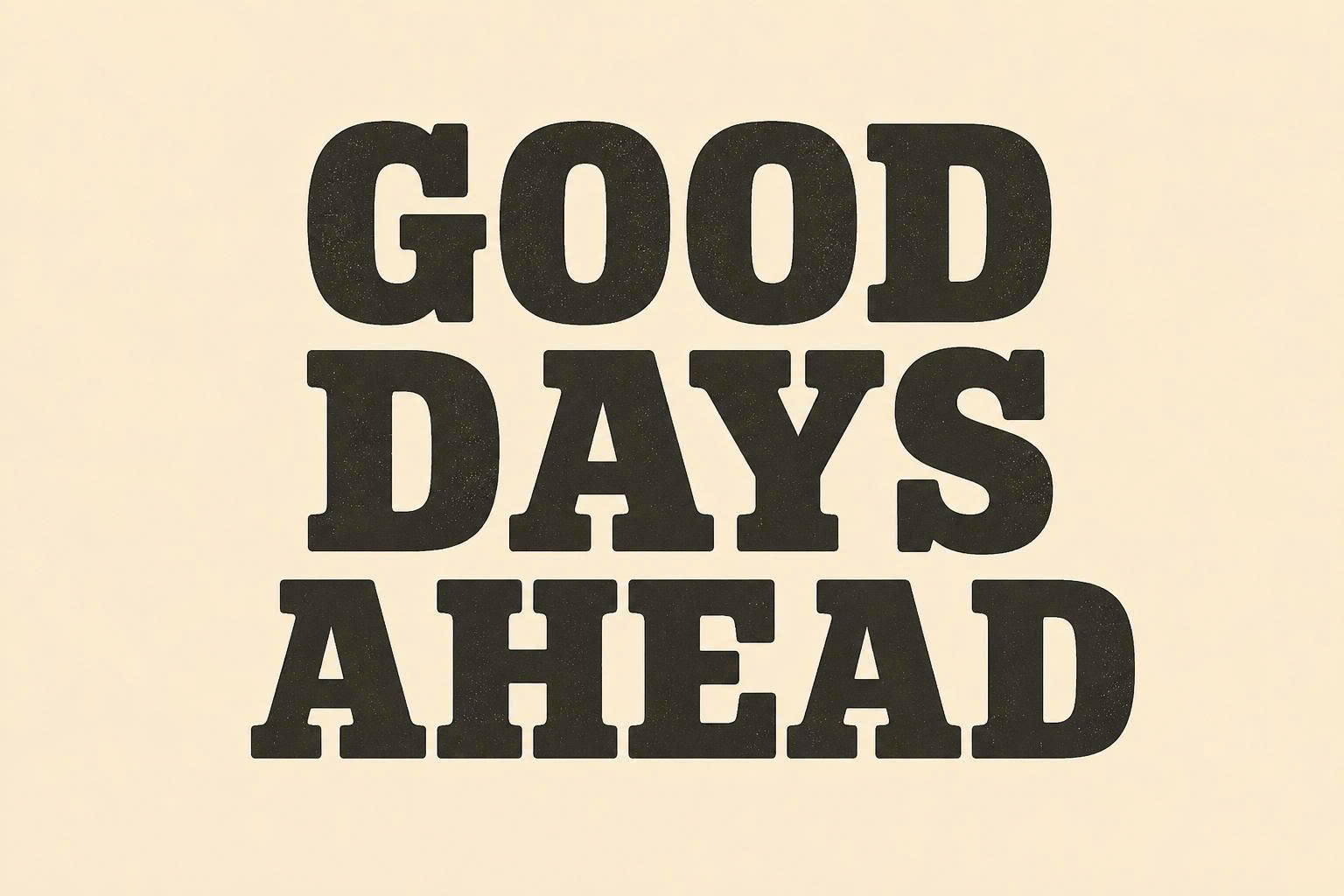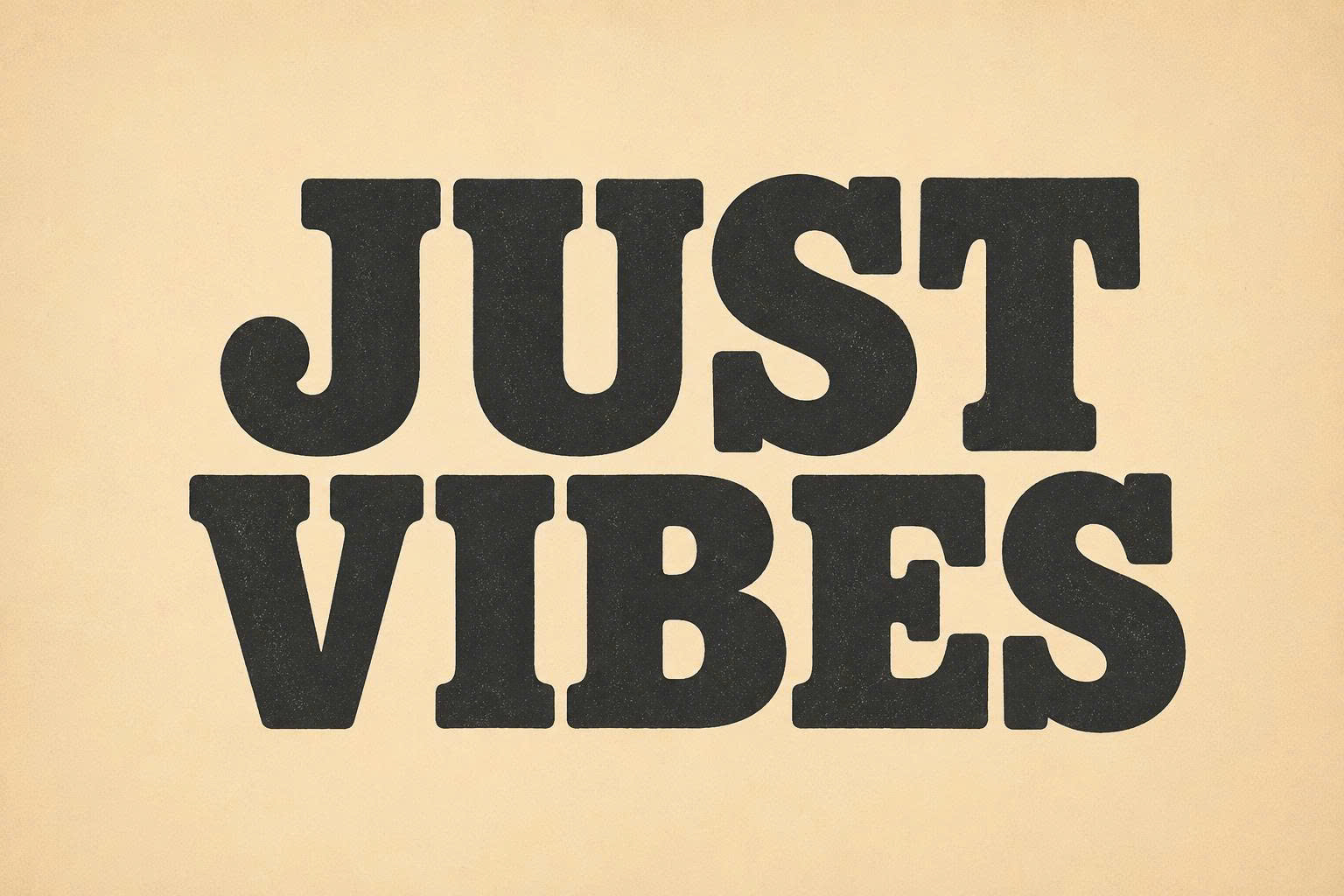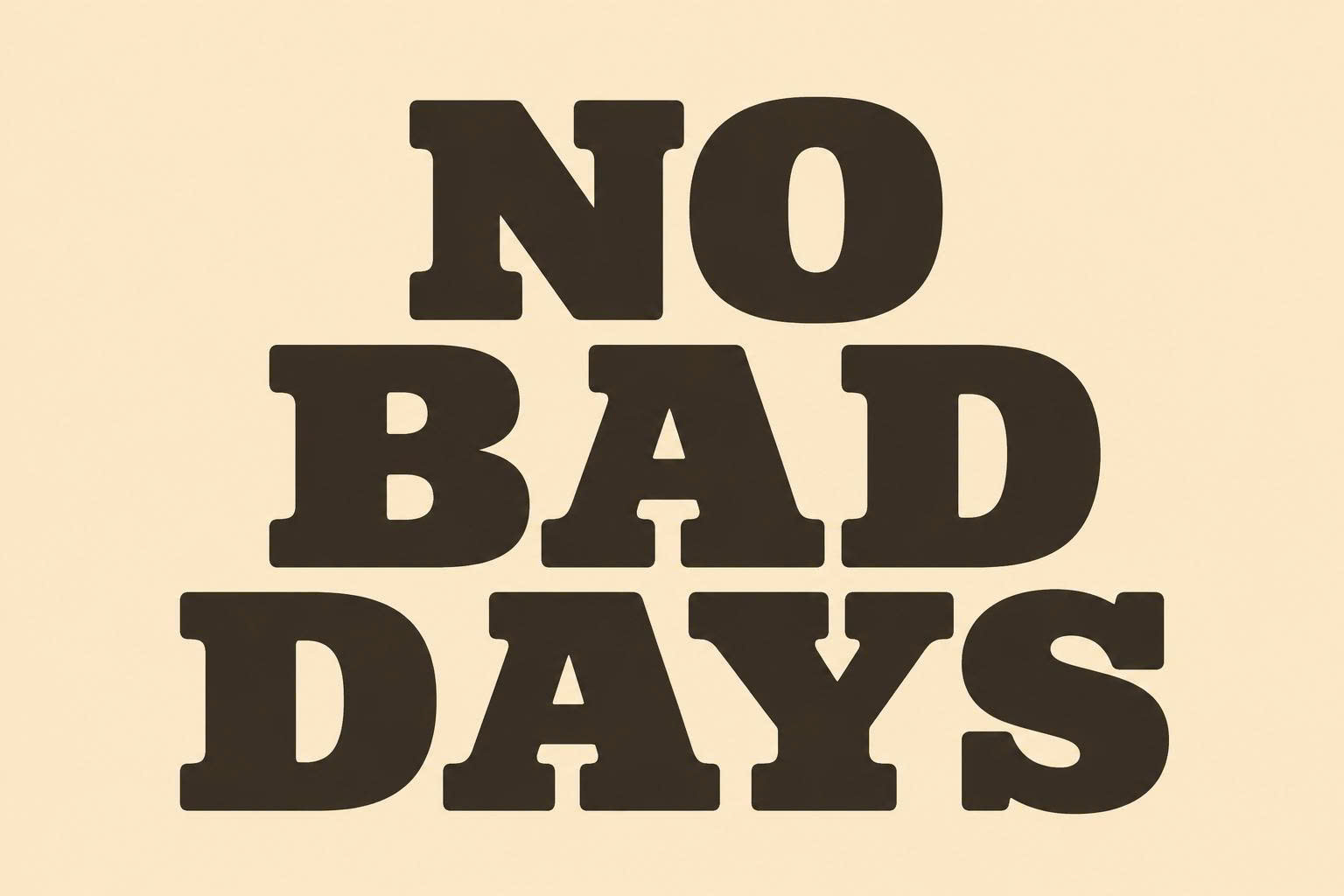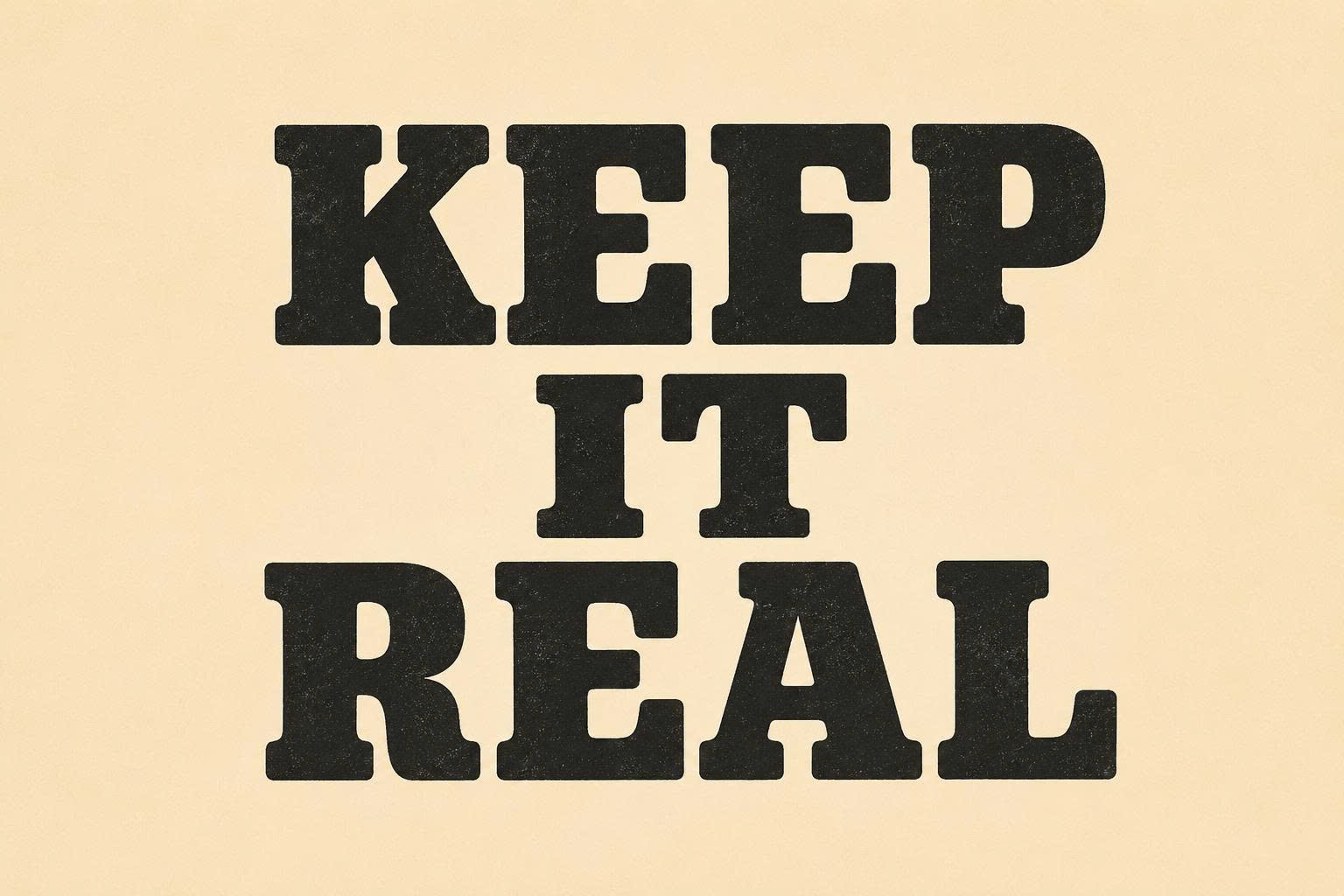
Đặc điểm thiết kế ấn tượng của font Aachen Việt hóa
Aachen không chỉ đơn thuần là một bộ phông chữ đậm; nó là biểu tượng của sự chắc chắn và quyền lực trong giới typography toàn cầu.
Phong cách Slab Serif mạnh mẽ và vững chãi
Đặc trưng lớn nhất của bộ font này là các nét gạch ngang (serif) dày và vuông vức, tương xứng với độ dày của thân chữ. Cấu trúc này tạo nên một khối văn bản vô cùng vững chãi, mang lại cảm giác uy tín và bền bỉ. Khác với các dòng Serif thanh mảnh, Aachen tạo ra một diện mạo nam tính, phù hợp cho những thương hiệu muốn khẳng định vị thế dẫn đầu trên thị trường.
Khả năng hiển thị vượt trội cho các tiêu đề lớn
Nhờ độ dày nét (Weight) cực lớn, Aachen duy trì được độ sắc nét và dễ đọc đáng kinh ngạc ngay cả khi người dùng quan sát từ khoảng cách xa. Khi được Việt hóa tại Doozypack.vn, hệ thống dấu tiếng Việt được tinh chỉnh để không làm tăng chiều cao của dòng chữ một cách quá mức, giúp bố cục thiết kế luôn cân đối và chuyên nghiệp.
- Tăng cường hiệu ứng thị giác: Với độ Bold tự nhiên, Aachen giúp tên thương hiệu trên túi giấy hay hộp quà nổi bật hoàn toàn mà không cần thêm quá nhiều hiệu ứng đồ họa phức tạp.
- Tính linh hoạt: Dù mang nét cổ điển nhưng Aachen vẫn hoạt động hiệu quả trong các thiết kế hiện đại nhờ cấu trúc chữ tối giản và rõ ràng.